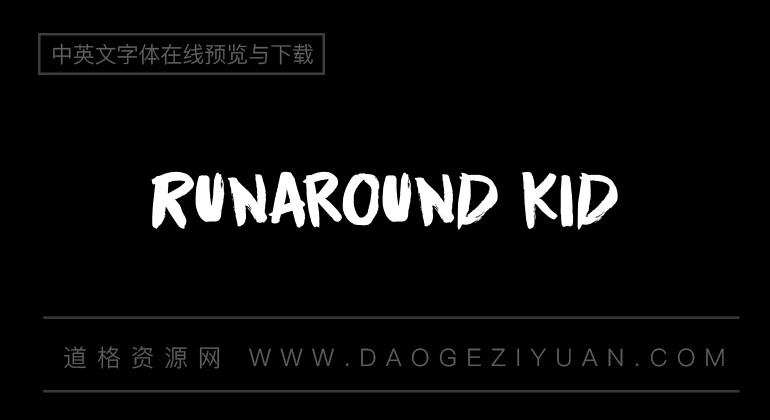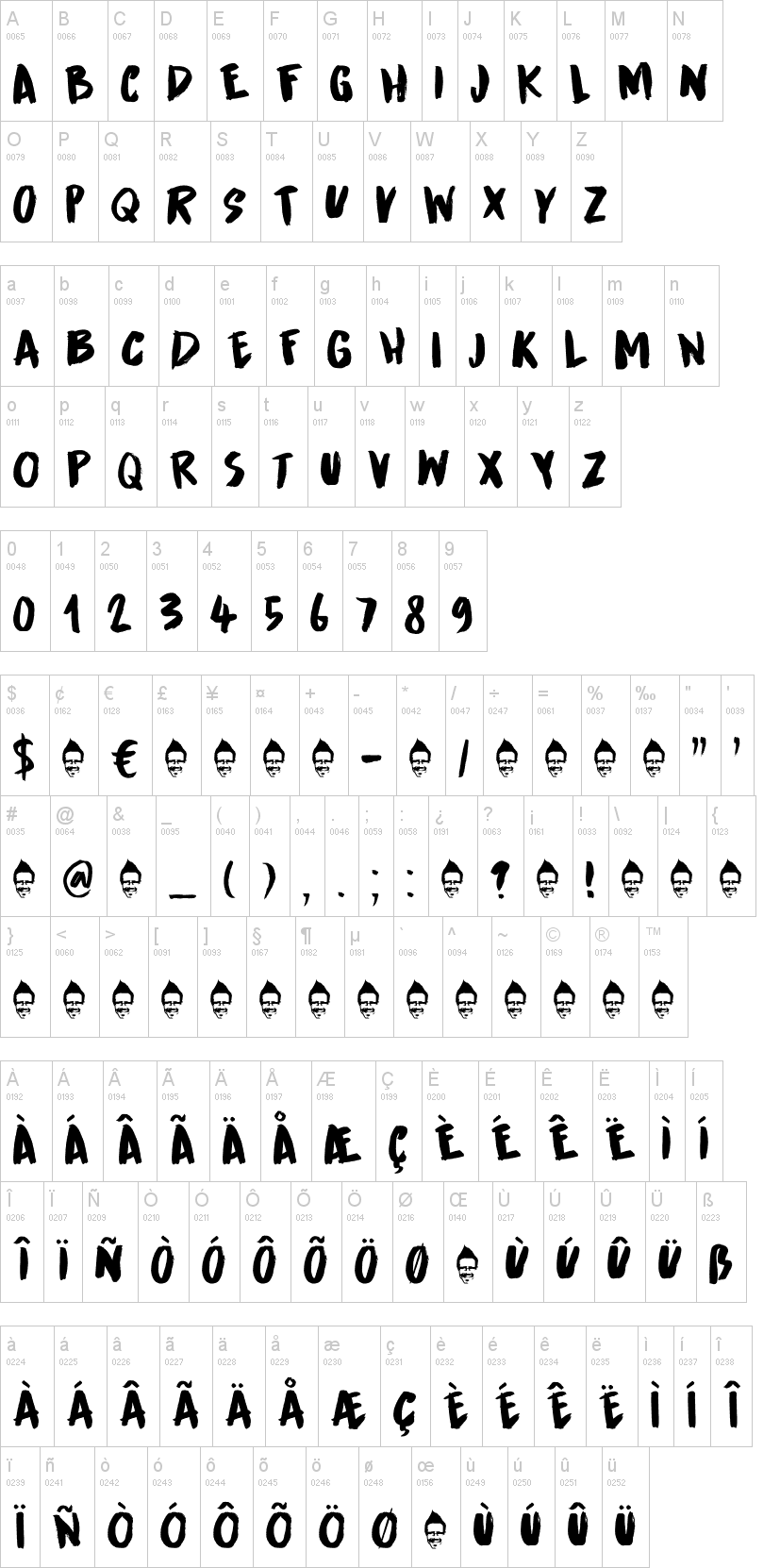
Runaround Kid 是一款经典的英文字体,由著名的英国设计师Paul Lloyd设计,于2004年发布。它具有独特的活力,是一种非常细腻的手写字体,具有较强的节奏感,能够传达出一种活泼有趣的气氛。它可以用于标题、标签、标语等,也可以用于报纸、杂志、海报等印刷品的设计,可以增加设计的趣味性和视觉冲击力。内容介绍
Runaround Kid是一款非常不错的手写艺术字体,具有很好的视觉感,适合于文化类的宣传设计、商业类品牌的广告和产品包装设计以及个性化文字排版等较多场景。